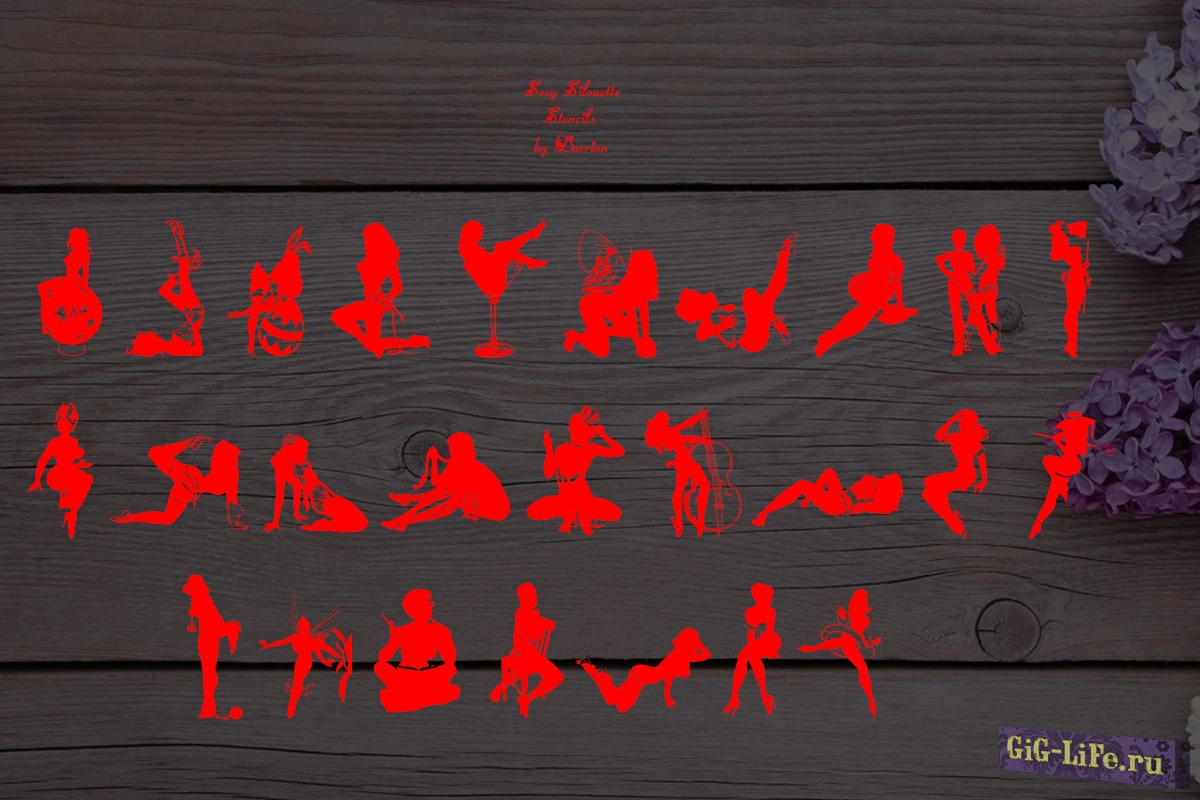
Сексуальные силуэтные шаблоны / Sexy Silouette Stencils - это соблазнительный способ использования эротического шрифта в программе Photoshop и других творческих проектах, основанных на символах.